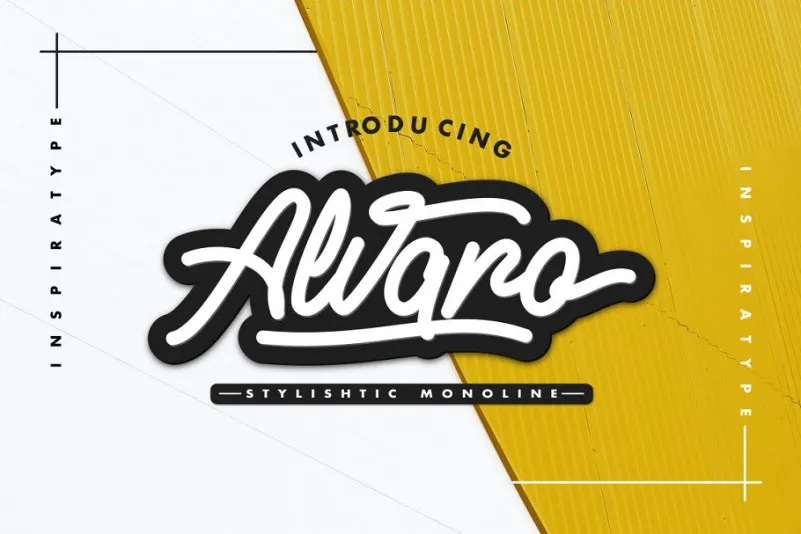
Alvaro Stylistic Monoline Font – Download Grátis
Alvaro Stylistic Monoline é uma fonte script monolínea de alta qualidade inspirada em estilos vintage e aventurais, oferecendo swashes que adicionam um toque único ao seu design. Se você está procurando por uma fonte de tipo vintage script cuidadosamente elaborada para suas criações gráficas, essa é a fonte perfeita. Alvaro Stylistic Monoline não é apenas um design elegante e moderno; ele é feito à mão com inspiração em clássicos de cartazes. A fonte vem com letras maiúsculas e minúsculas, números e pontuação, além de variações únicas para cada caractere que incluem alternativas de OpenType, ligaturas comuns e ainda mais swashes. Isso lhe permite personalizar seus designs de forma impressionante. Ideal para o uso em logotipos, cartões de atendimento, panfletos, roupas, rótulos e muito mais. Alvaro Stylistic Monoline é uma fonte perfeita para quem deseja adicionar um toque diferenciado a suas criações gráficas, mantendo o estilo vintage moderno que tanto apreciamos nos nossos dias contemporâneos.